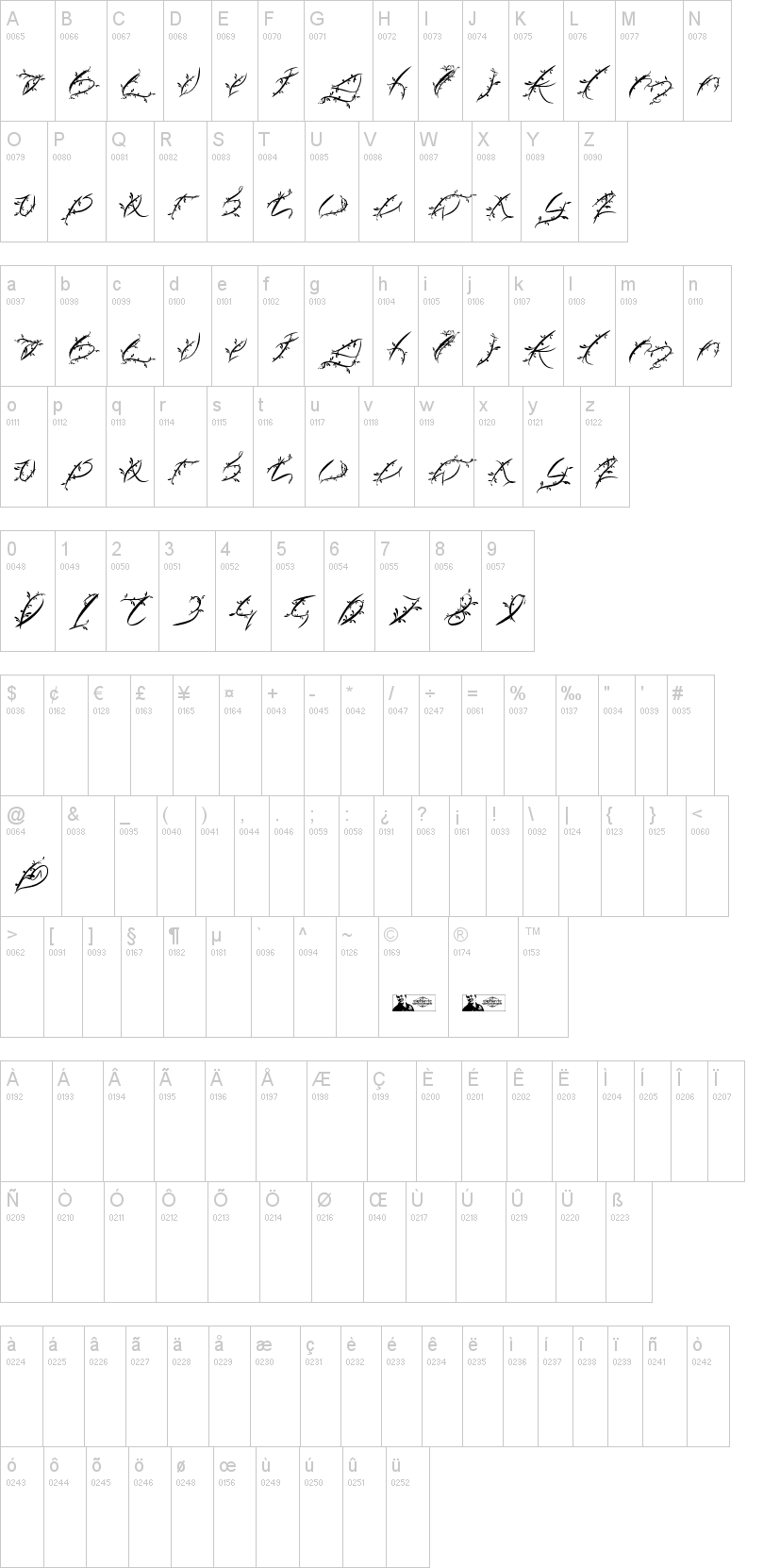
? FTF Leafy Lopstonesia字体是一款强调自然美感的草书字体。它是一款结合了英国古典风格和日本書法风格的字体,它的特点是细节丰富、笔画流畅、线条优美,有着优雅的曲线和清新的节奏。它的字形结构设计得非常精致,可以让您的文字更加精致而优雅。它的字体设计具有英国古典风格和日本書法风格的结合,可以让您的文字更加精致而优雅。它适用于很多种类的文字,如设计、报纸、书籍、海报等,可以让您的文字更加有个性。内容介绍
FTF Leafy Lopstonesia是一款非常不错的手写艺术字体,具有很好的视觉感,适合于文化类的宣传设计、商业类品牌的广告和产品包装设计以及个性化文字排版等较多场景。